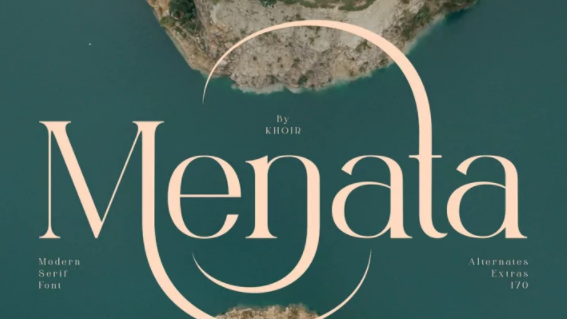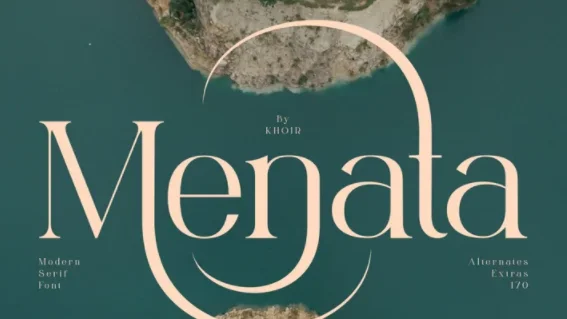
Название: Menata Font (2022)
Представляем Menata - Serif классический Современный уникальный, в каждой букве есть красивая связь и соотносятся друг с другом, Этот шрифт поддерживается специальными и многоязычными альтернативами, которые являются довольно полными, имеет 170 интересных альтернатив, что делает этот шрифт универсальным и хорошо работает в различных размерах. Этот шрифт идеально подходит для логотипов, брендинга, дизайна, приглашений, романов, книг, журналов, этикеток, поздравительных/свадебных открыток. Так чего же вы ждете!
Название: Menata Font (2022)
Представляем Menata - Serif классический Современный уникальный, в каждой букве есть красивая связь и соотносятся друг с другом, Этот шрифт поддерживается специальными и многоязычными альтернативами, которые являются довольно полными, имеет 170 интересных альтернатив, что делает этот шрифт универсальным и хорошо работает в различных размерах. Этот шрифт идеально подходит для логотипов, брендинга, дизайна, приглашений, романов, книг, журналов, этикеток, поздравительных/свадебных открыток. Так чего же вы ждете!